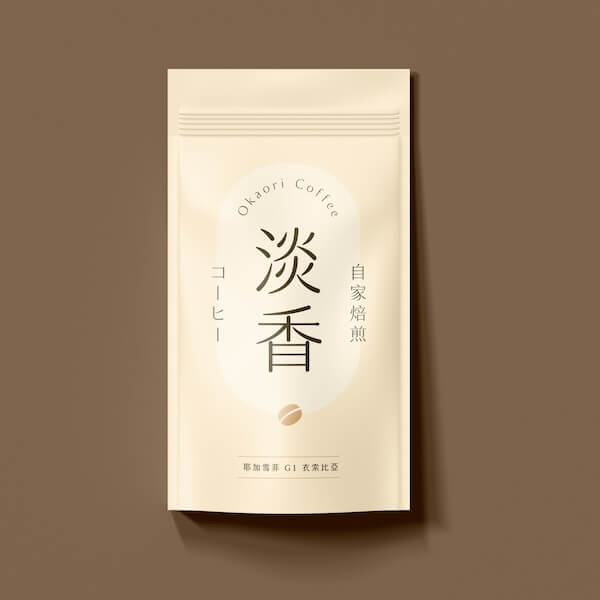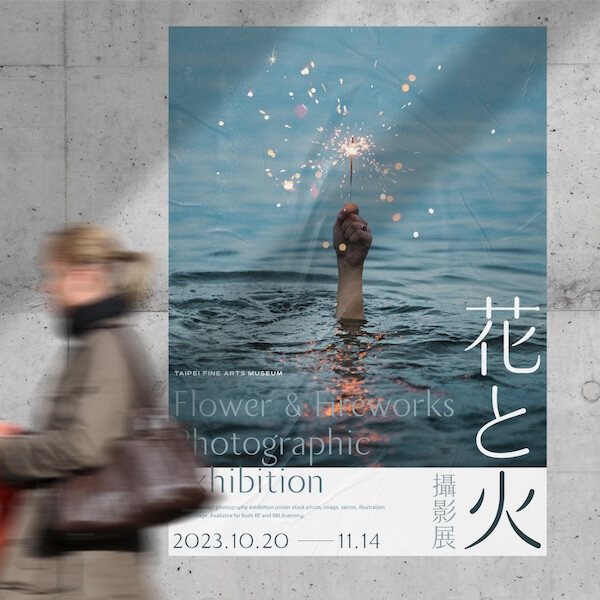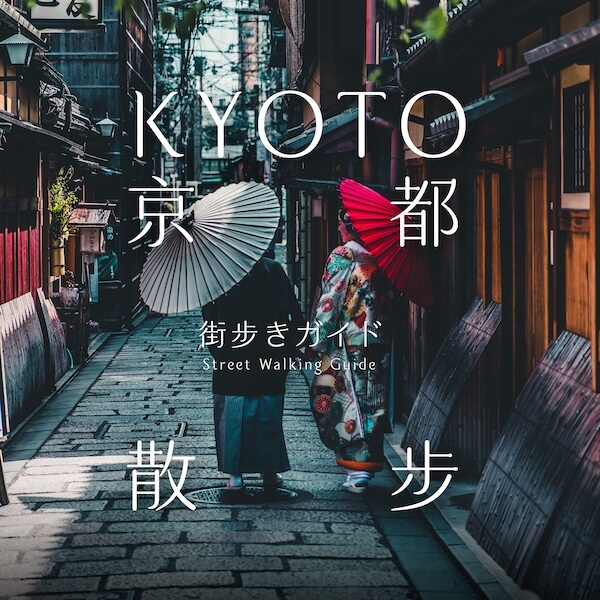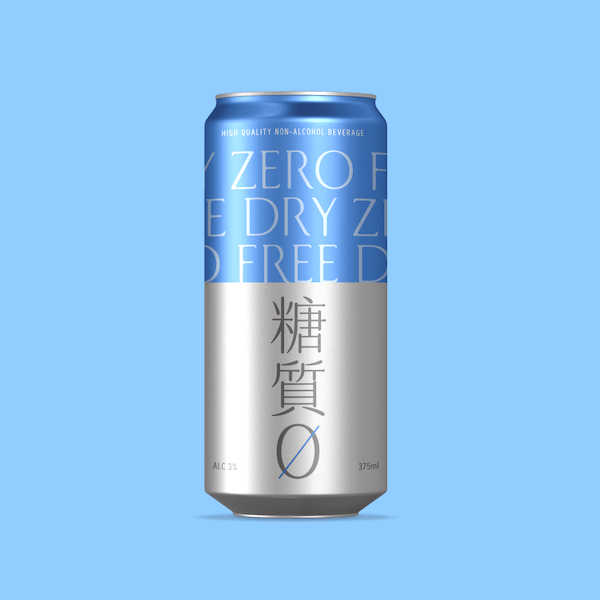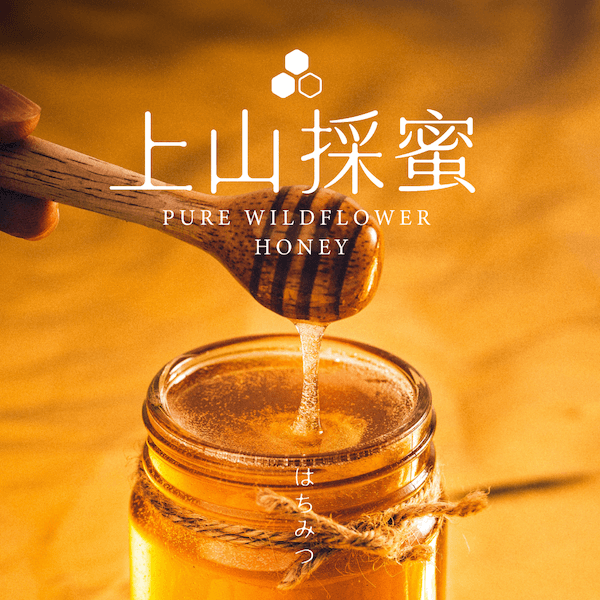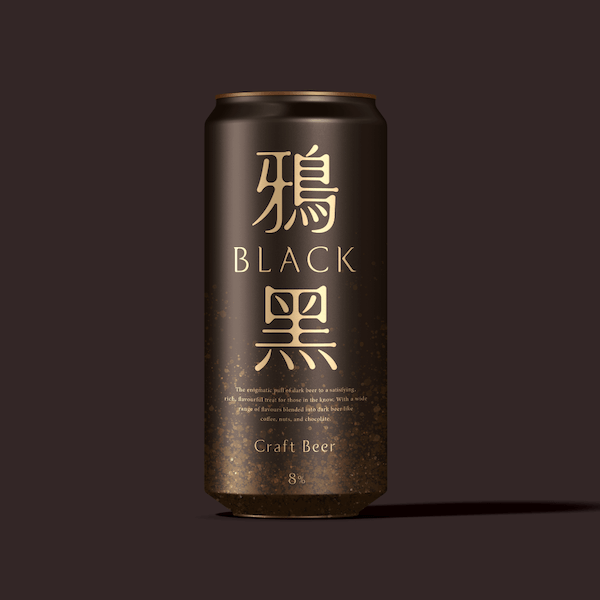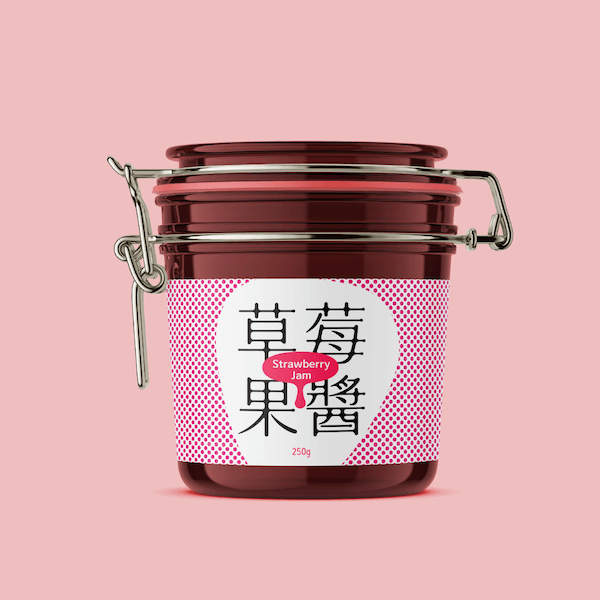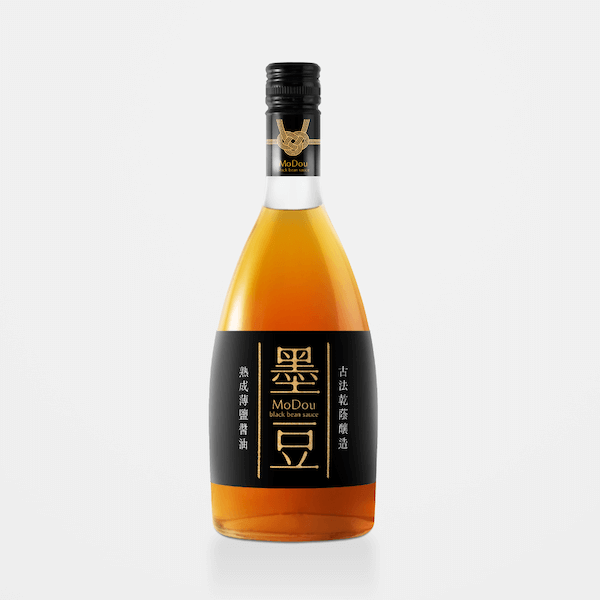
淚體
有情緒流露著,卻不過於張揚。
曖昧朦朧,是淚體最吸引人的地方。
- 楊宗烈
字型設計師
Alen Yang
平面設計師。一天三杯咖啡。覺得睡覺浪費時間。不太擅長聊天。 左右腦發展勢均力敵,理性與感性誰也不讓誰。沒有信手捻來的功力,靠用心感受思考與練習。 不喜歡為了設計而設計。喜歡看起來沒有設計的設計。